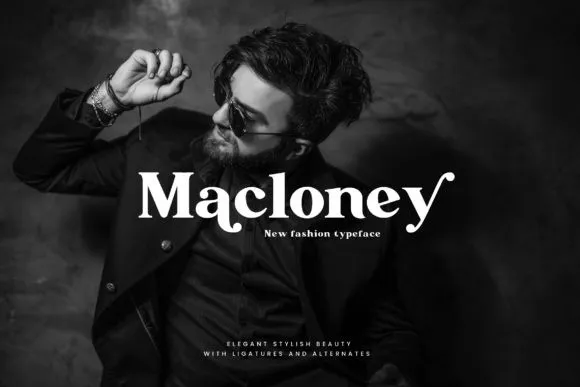
A fonte Macloney é uma tipografia séria desenvolvida para oferecer equilíbrio perfeito entre os ramos grossos e as travessas finas, criando um estilo único e versátil que se destaca como uma excelente opção para vários fins de uso. Esta fonte foi projetada especificamente para ser usada em magazines, logos, embalagens de papelaria, compartilhamento de citações nas redes sociais, moda e muito mais. Com seu suporte multilíngue, alternativas maiúsculas inclusas e ligaduras incorporadas, a Macloney oferece um conjunto completo de recursos para atender às necessidades dos criadores de conteúdo modernos. Seja você um designer ou um editor de texto, a Macloney traz uma nova qualidade à sua produção, com seu formato de letra elegante e arquitetura robusta que se adapta perfeitamente aos mais diversos ambientes digitais.